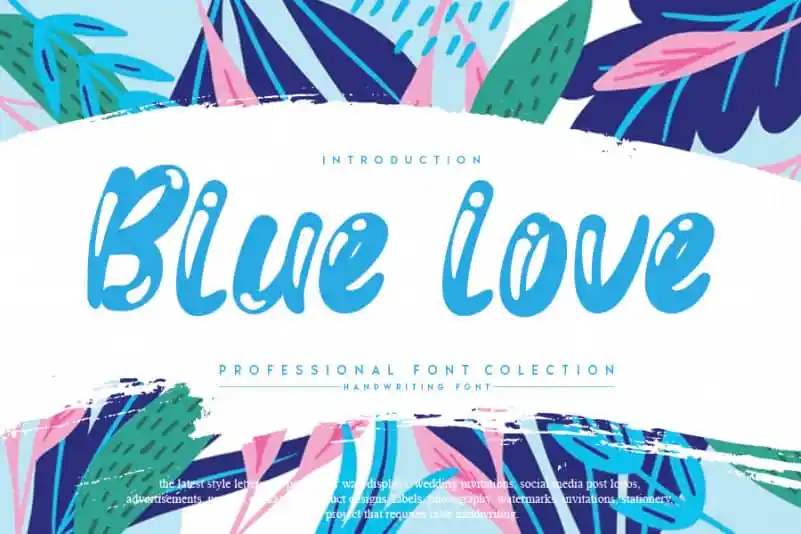
A Blue Love Display Font é uma elegante fonte escrita a mão que traz consigo um toque cálido e descontraído. Ideal para quem procura expressar amor e carinho de forma natural e criativa, seja através das postagens no Instagram ou dos projetos personalizados em calligrafia, essa fonte pode transformar quaisquer ideias únicas e originais num verdadeiro artefato. Com um toque delicado e uma aparência encantadora, Blue Love é perfeita para aqueles que buscam uma fonte agradável para dar vida à sua criatividade, seja em design de logotipo ou letras livres.